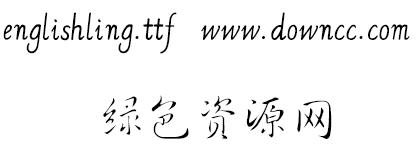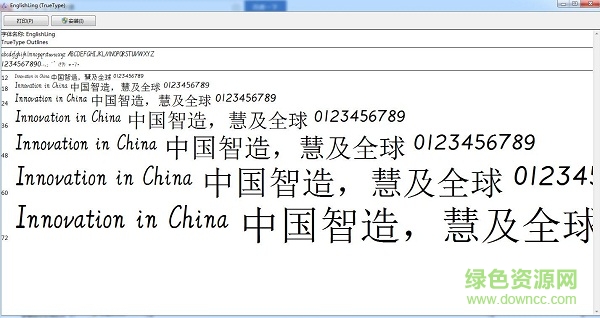
英語手寫書寫字體englishling.ttf是一款漂亮優(yōu)雅的高品質字體,字形清秀,線條流暢,親切又美觀,從事廣告設計或平面設計的朋友都用得上這款手寫體,歡迎免費下載!
【圓體】
這種字體,含有國外copperplate(銅板印刷體)等的一些結構特點,以及筆畫的銜接,普通的鋼筆即可書寫,較為快速、圓滑。
【意大利體】
這種字體,有一定的斜度和筆畫的線條的粗細變化,需要稍微粗一點兒的鋼筆書寫,也是市場上常見的字帖一類的教材的標準字體。
【手寫印刷體】
這種字體簡單易懂,寫出來很好,是現(xiàn)在國內外常用的日常手寫字體。